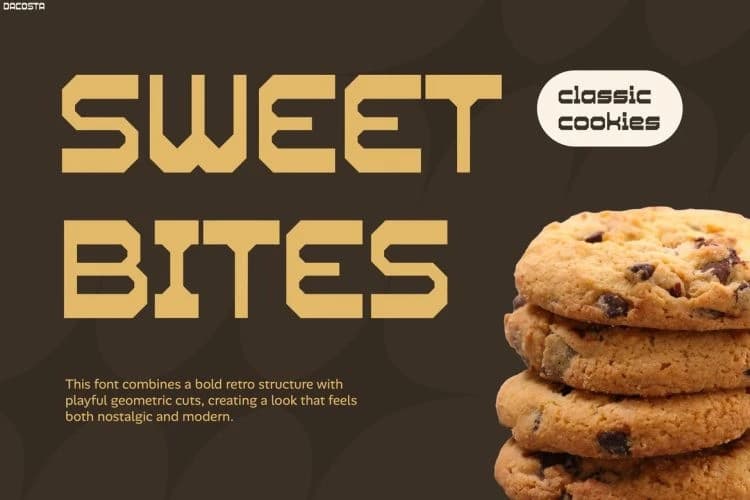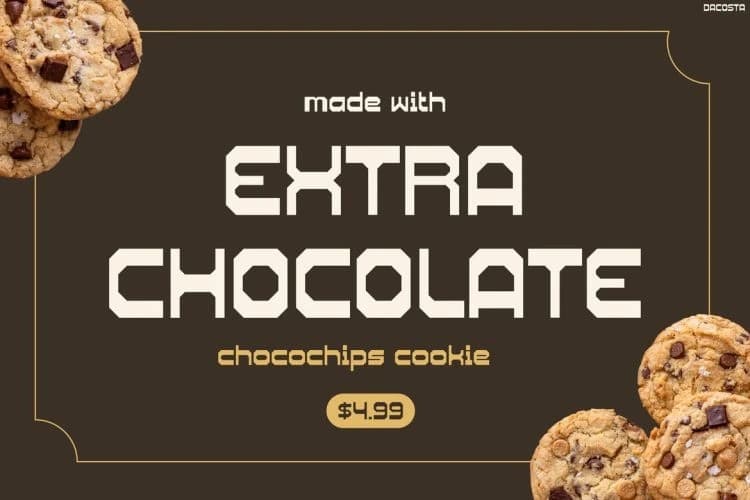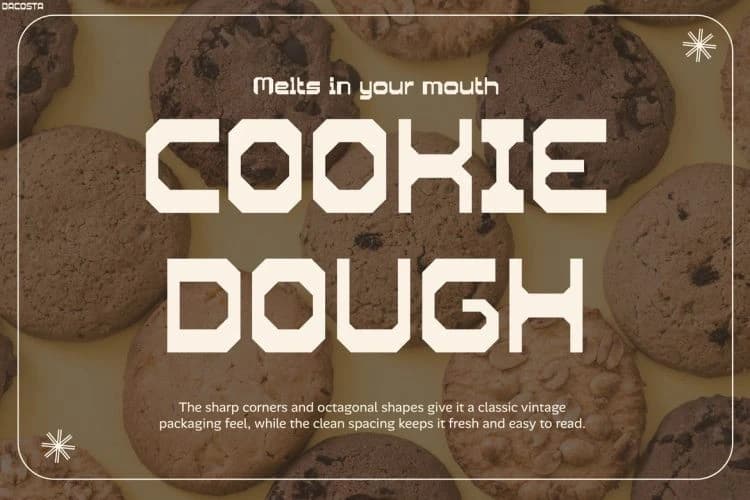
Dacosta Display Font
Dacosta Display Font, retro estetiği ile modern geometrik hassasiyeti birleştiren geleceğe yönelik bir gösterim yazı tipidir. Eski teknoloji, siber görseller, arcade kültürü ve cesur ambalaj tasarımından esinlenen bu yazı tipi, anında güçlü ve şık bir görsel kimlik yaratır.
Dacosta Display Font, retro estetiğini modern geometrik hassasiyetle birleştiren gelecek vaat eden bir gösterim yazı tipidir. Eski teknoloji, siber görseller, arcade kültürü ve cesur ambalaj tasarımından ilham alan bu yazı tipi, anında güçlü ve şık bir görsel kimlik oluşturur.